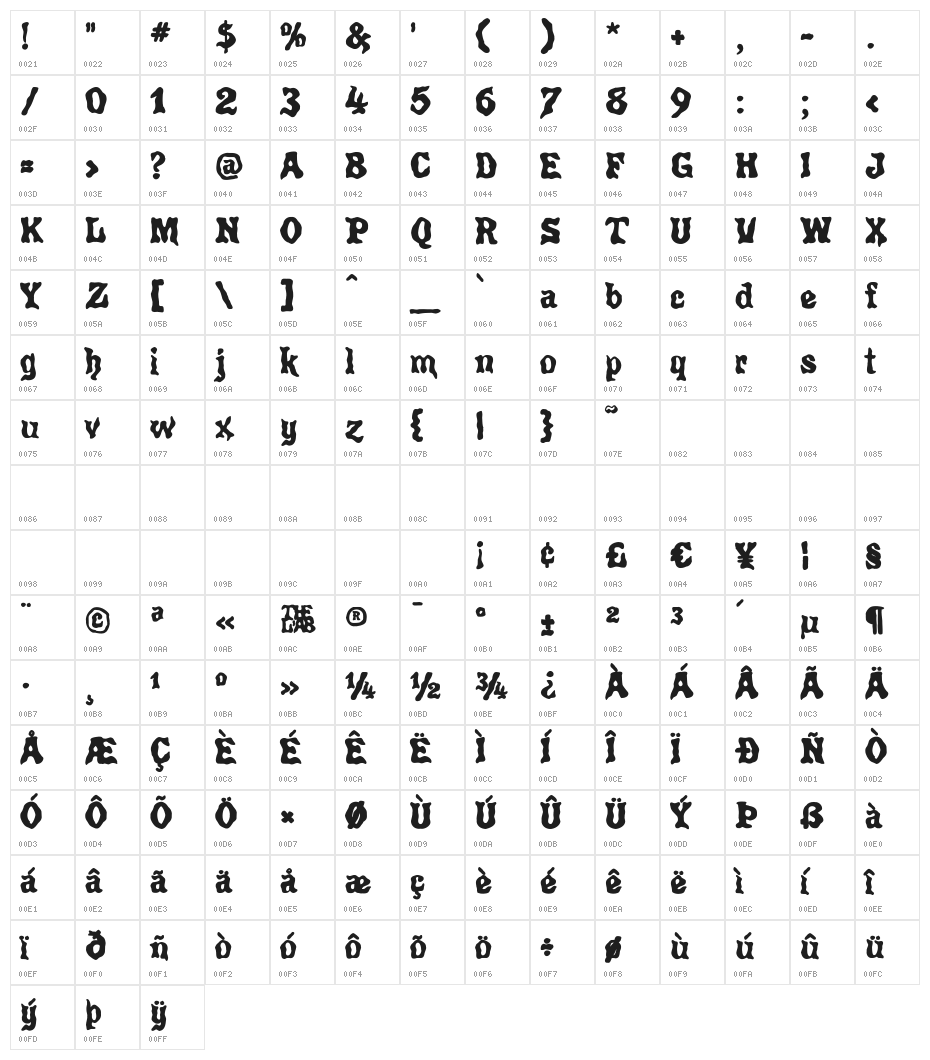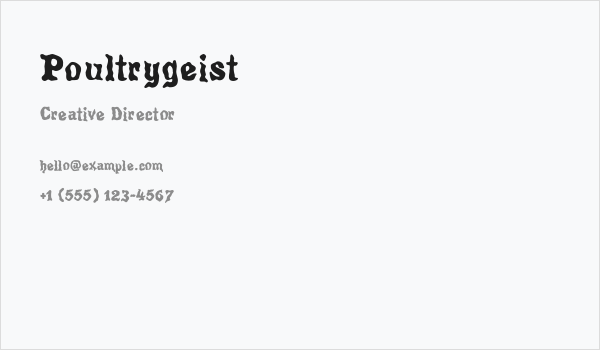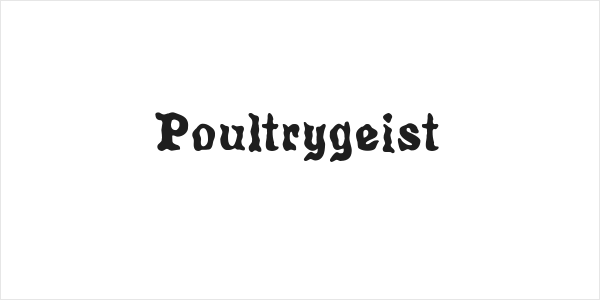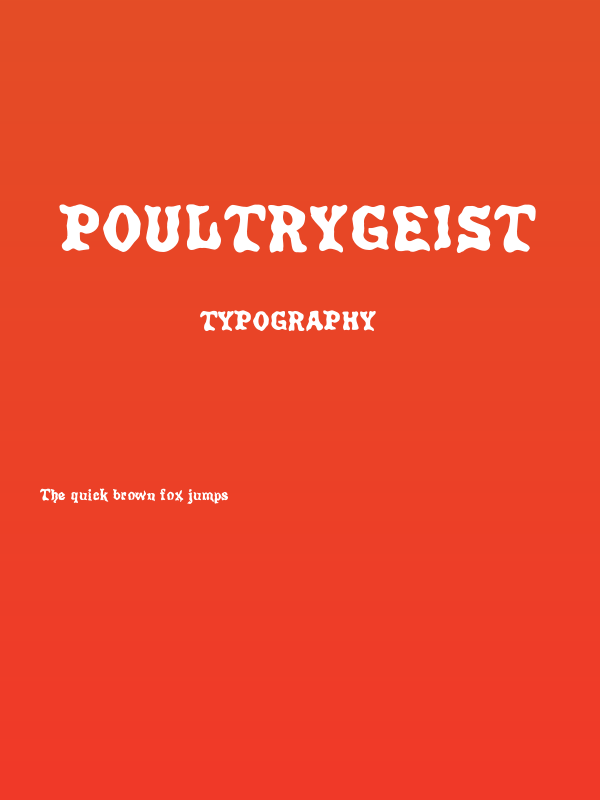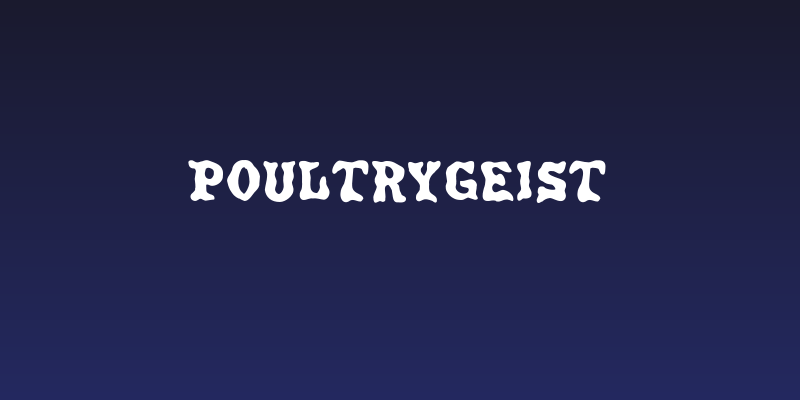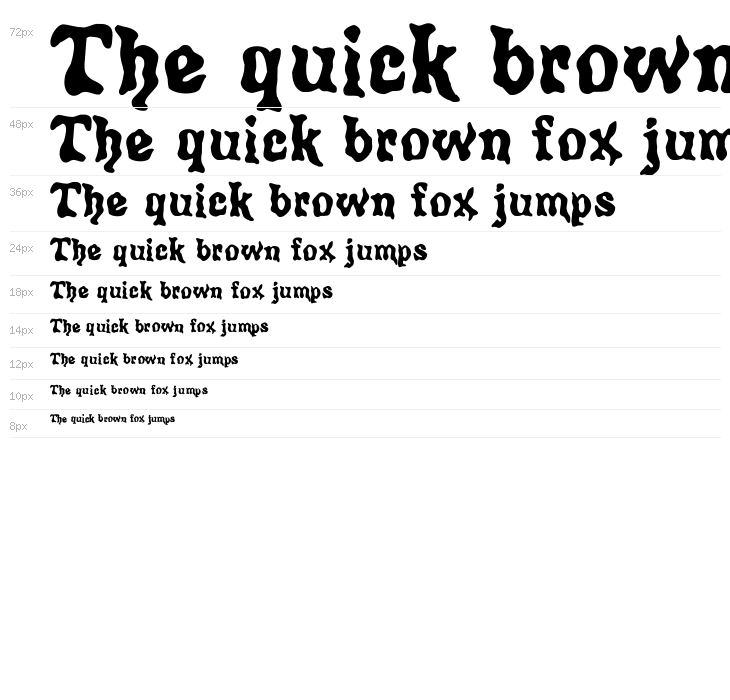
Poultrygeist Font
Fonts by Apostrophic Lab
| Vorgeschlagene Projekte | Ideal for Halloween-themed designs, children's book covers, playful posters, and creative branding projects. |